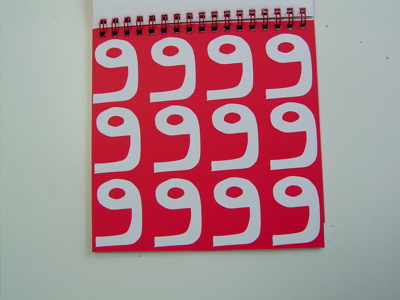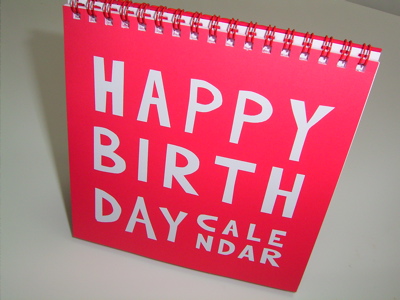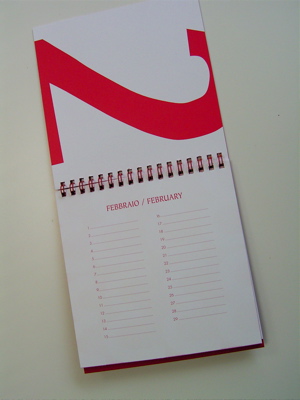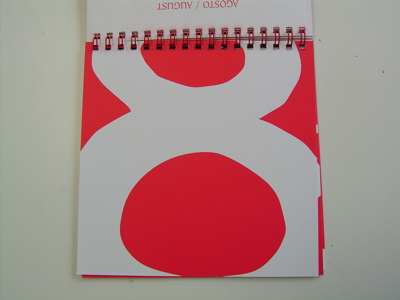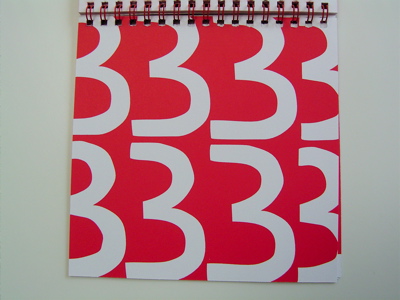
バースデーカレンダーみっけ
見つけました!バースデーカレンダーです。
文字がいいでしょう!書いたと言うより切りぬいて貼ったみたい。
中はいたってシンプル。日にちの所に名前が書ける様になっているだけです。実用的。
私が最も気に入ったのは、月の数字のデザインがおもしろいところです。横向きだったり、たくさんだったり、はみ出たり。
よく見るとすべて同じ形ではないから、ひとつひとつ書いたのか切り取ったのか。
色が白と赤だけというところがいいね。私の生まれ月の3月が可愛いのますます嬉しい。